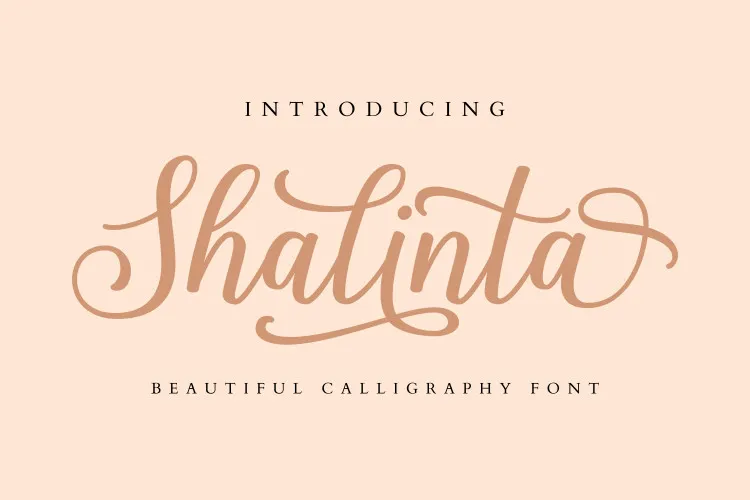
A fonte Shalinta Calligraphy é perfeita para quem busca uma nova face tipográfica no estilo calligráfico para seus projetos. Esta fonte apresenta um charme único, com 359 caracteres incluídos que cobrem os padrões estilísticos de escrita e suportam várias línguas, o que a torna uma opção versátil. O conjunto de alternativas adicionais oferecido pela Shalinta não só dá ao design um toque refinado, mas também permite adaptar sua visão artística de forma única, tornando-a ainda mais atrativa e interessante. Este é um recurso valioso para designers que procuram fazer seus projetos se destacarem em uma série de ambientes digitais.